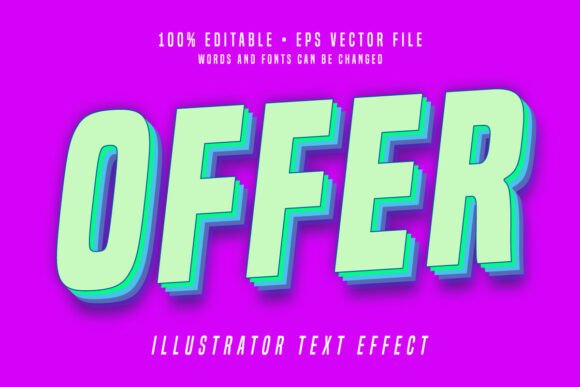
Offer 3d Editable Text Effect Bold Font
Пошук відповідних елементів дизайну може бути складним, але Offer 3d Editable Text Effect Bold Font пропонує виняткову колекцію, яка миттєво покращить вашу роботу.
Створений з високою точністю, Offer 3d Editable Text Effect Bold Font забезпечує чисті вектори, плавну типографіку та комерційну ліцензію для вашого спокою.
Незалежно від того, чи створюєте ви продукти POD (друк на вимогу), весільні запрошення або графіку для соціальних мереж, Offer 3d Editable Text Effect Bold Font стане ідеальним вибором.